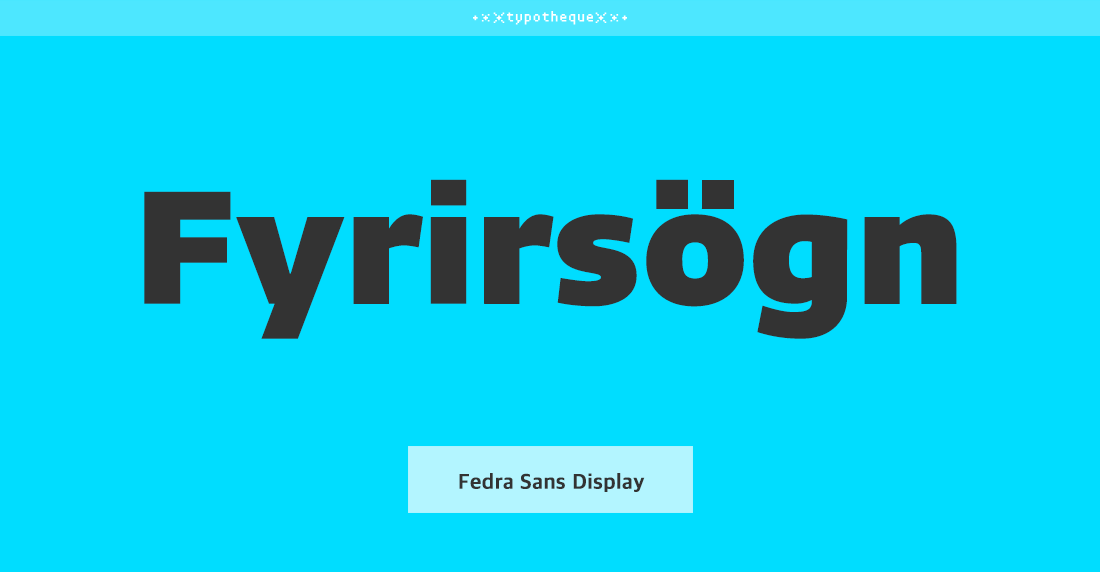
- Fedra Sans Display Std는 공간이 제한적이고 현대적인 인상을 필요로 하는 헤드라인에 어울리는 폰트이다.
매우 가는 Hairline부터 무게감이 느껴지는 Black까지 다양한 웨이트가 있어 범용적으로 사용하기 좋다.
폰트 정보 폰트명 Fedra Sans Display Std 구분 고딕 디자인디렉팅 Peter Biľak, Pieter van Rosmalen, Vera Ecstafieva 출시년도 2005